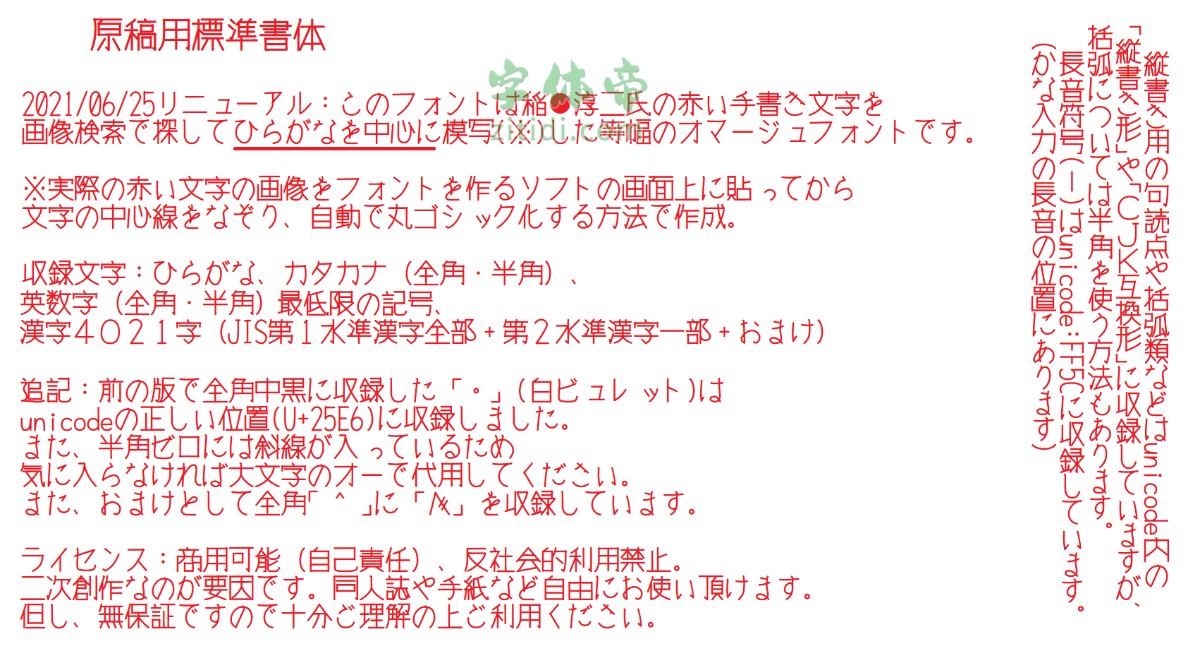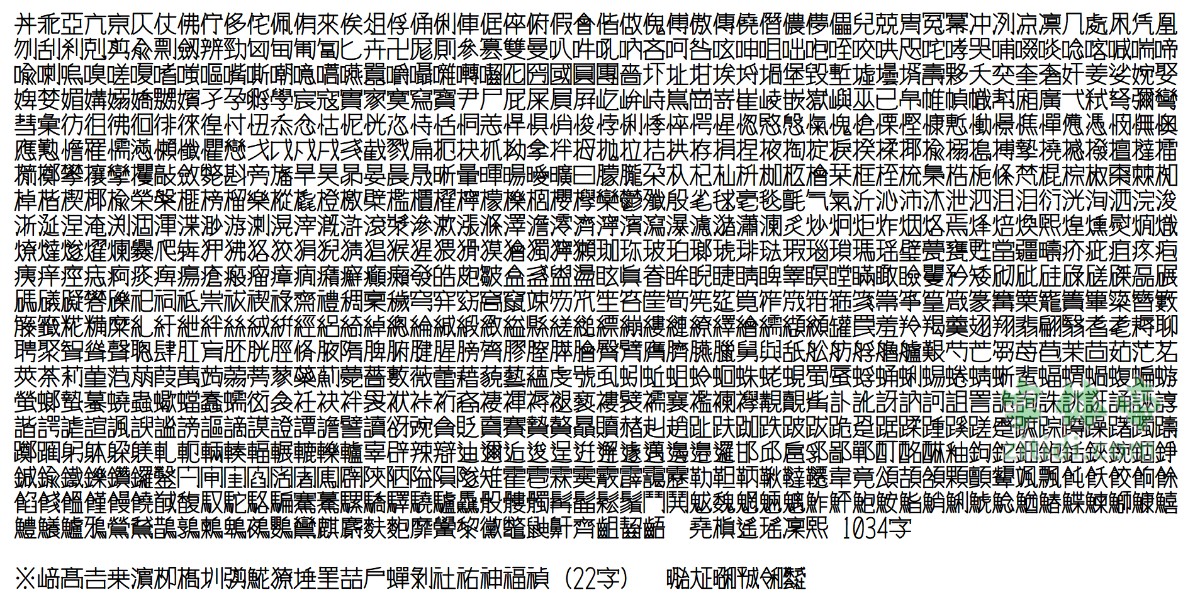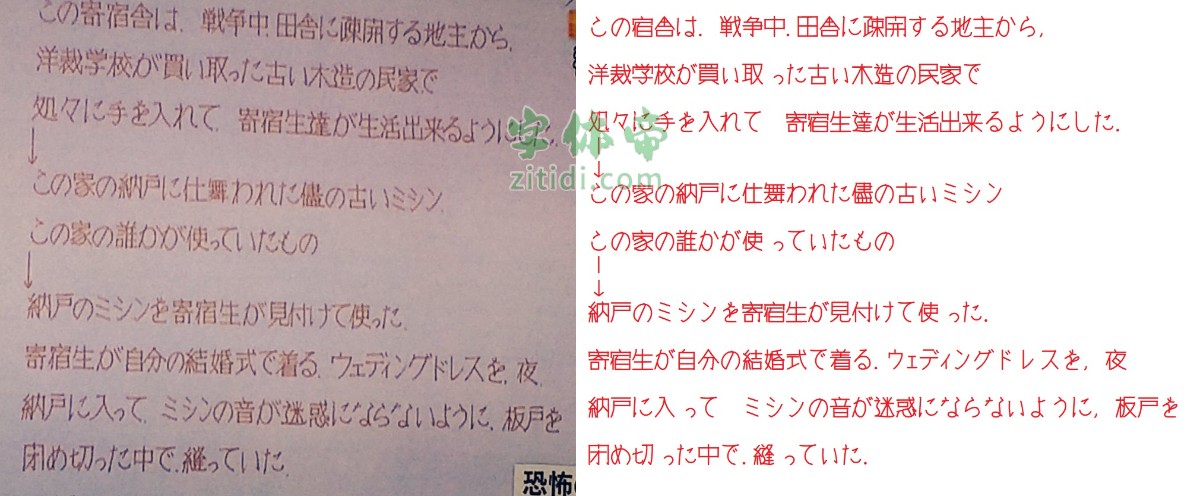
原稿用標準書体字体信息
原稿用标准书体这个字体简单来说就是稻子●淳二风丸风格的手写字体。这款日系手写字体颇有特色,但可惜的是只支持JIS第一水准汉字+部分JIS第二水准汉字,所以简体字数不多。而繁体字数也是勉强够用。大家喜欢的话可以下载。
“原稿用標準書体”是一款书写很新颖的字体,字体大方,适合各种设计作品使用!欢迎下载!